モリサワが和文デザイン書体やグローバルな情報発信にも対応できる多言語書体などの2024年度新書体を追加発表
モリサワは、2024年度新書体として、すでに発表済みの写研フォントや当社初の和文バリアブルフォント「DriveFlux」に加えて、世界観づくりにぴったりな和文デザイン書体やグローバルな情報発信にも対応できる多言語書体など、合わせて140以上のファミリーをリリースすることを2024年9月4日 に発表した。
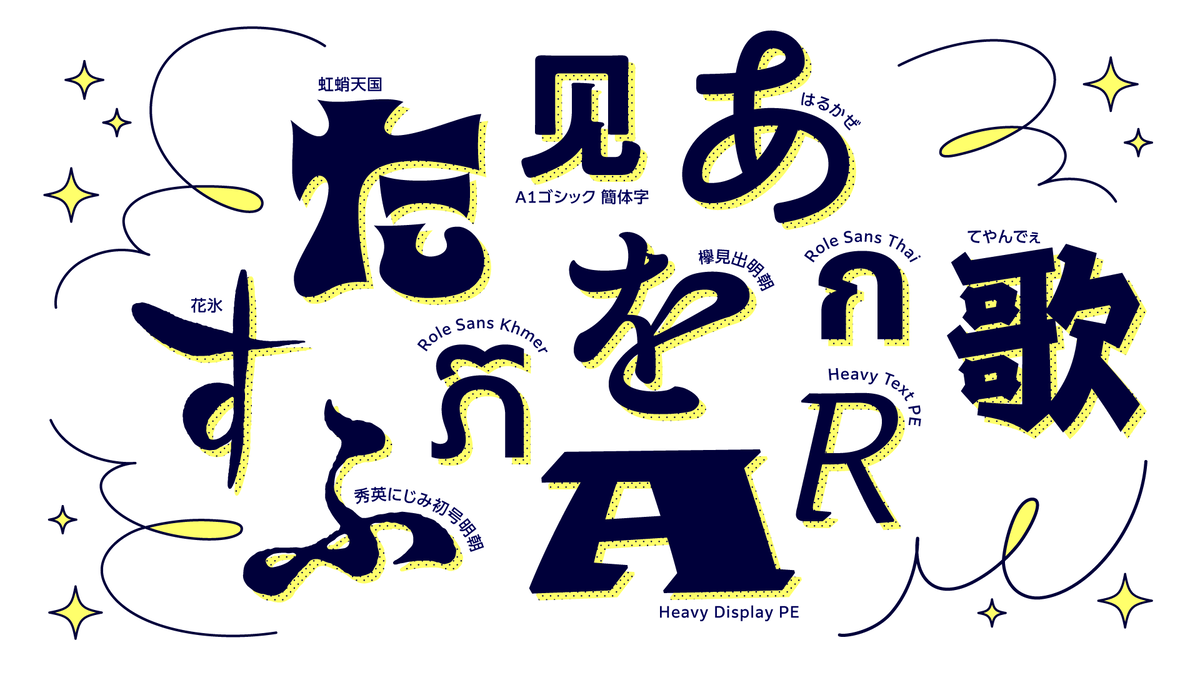
2024年度では、サイケデリックなアートや音楽からインスパイアされた極太の「虹蛸天国(にじたこてんごく)」のほか、丸い輪のような装飾が楽しげな印象を与える「はるかぜ」、江戸文字からインスパイアされた「てやんでぇ」など、世界観づくりにぴったりなデザイン書体をリリースする。
さらに書家による毛筆の文字が元となった「花氷(はなごおり)」など、華やかな筆文字系デザイン書体の選択肢が広がった。
明朝体には、2023年にリリースした「欅(けやき)明朝 Oldstyle」の見出し書体「欅見出明朝」や、人気の「秀英にじみ」シリーズから「秀英にじみ初号明朝」などを新たに追加。
ユニークなファミリー展開が特徴の「Heavy」シリーズなど、デザインに彩りを加える特色豊かな欧文書体にも注目。
そのほか、グローバルな情報発信にも対応できる多言語フォントがより充実した。
オールドスタイルのゴシック体「A1ゴシック」に簡体字や繁体字が、欧文スーパーファミリー「Role」にインドと東南アジアの主要な種類の文字に対応する多言語展開ファミリーが、それぞれ登場。
SCREENグラフィックソリューションズのヒラギノフォントには、人気書体「こぶりなゴシック」の最も細いウエイト、W0が追加される。
2022年にモリサワグループの一員となった、台湾を代表するフォントメーカーArphic Typesからは、中国語の表現がより豊かになる簡体字・繁体字書体ラインナップを追加。
シンプルで可読性の高いユニバーサルデザイン(UD)書体「AR UDJingxiheiE1(アーフィックユーディージンシーヘイイーイチ)」や、柔らかくも力強い印象の「AR ShuYuanSong(アーフィックスーユェンソン) Text H32」などArphic Typesの代表書体が仲間入り。
また、温かみとリズミカルな動きを表現した「AR Mochi(アーフィックモチ) H16C90」や、近未来的な雰囲気の「AR Xinyi(アーフィックシンイー)」は、翠流(すいりゅう)シリーズのベースとなった書体です。和文書体「翠流きら星」や「翠流アトラス」などと合わせて使うことにより、日本語と中国語の両方を必要とする場面でデザインの統一感が生まれる。
アメリカに拠点を置くOccupant Fontsの欧文ライブラリも加わる。
Occupant Fontsは、タイプデザイナーとして長いキャリアを持ち、2017年からはモリサワUSAのクリエイティブディレクターとして活躍するサイラス・ハイスミス氏がリードする書体ライブラリとなる。
シンプルながら遊び心を感じさせる書体「Magmatic(マグマティック)」や「Zocalo Text(ソカロテキスト)」のほか、目を引く華やかなディスプレイ書体「Occupant Gothic(オキュパントゴシック)」や「Biscotti(ビスコッティ)」など、バラエティ豊かなラインナップを追加。
欧文組版の選択肢が増えることはもちろん、和文書体との混植や併記利用で、表現の幅も一段と広がる。